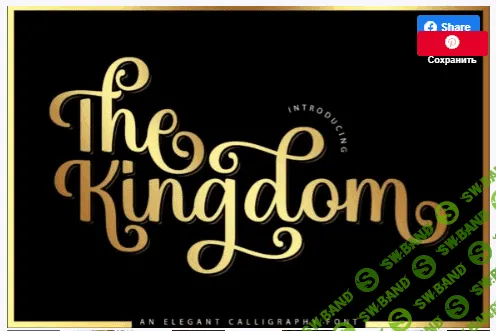
Название: The Kingdom Font (2021)
Королевство одинаково очаровательно и элегантно. Он потрясающе смотрится на свадебных приглашениях, открытках с благодарностью, цитатах, поздравительных открытках, логотипах, визитных карточках и любом другом дизайне, требующем рукописного ввода.